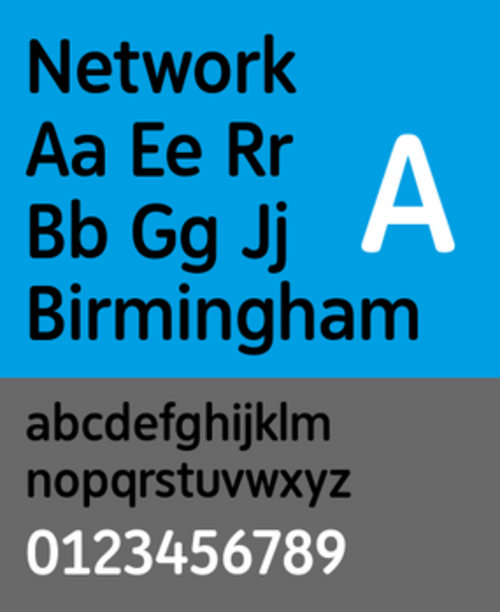
| カテゴリ | サンセリフ |
| 分類 | ネオグロテスク |
| デザイナー | ダン・ラティガン |
| 委託先 | ウェストミッドランズ交通局 |
| 作成日 | 2012 |
Networkは、もともとモノタイプ社がイギリスのバーミンガム/ウェストミッドランズ都市圏の交通網で使用するために作成したサンセリフ書体です。この書体は、ウェストミッドランズ旅客運輸局が同州の公共情報に使用していた書体であるVAG Roundedに基づいています。[1]
Networkは2018年まで交通機関のブランディングや標識に使用されていましたが、ウェスト・ミッドランズ交通局によって段階的に廃止され、ウェスト・ミッドランズ・メトロを含むさまざまな交通機関で新しい共通ブランディングが導入され、 LinetoのLL Circularが主要な書体として使用されました。[2] [3] [4]
- ジョンストン(書体) -ロンドン交通局がネットワークに似た形で使用している象徴的な書体。